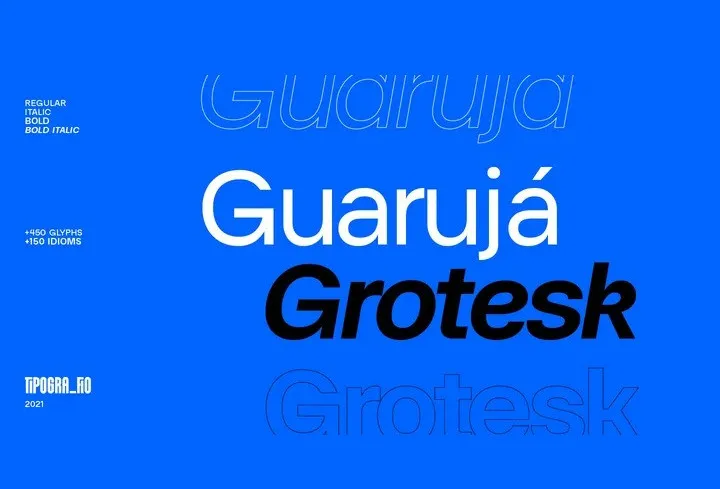
A Guaruja Grotesk Font é uma escolha perfeita para aqueles que desejam incorporar a clássica influência do Modernismo na linguagem visual, numa família de letra sans-serif geométrica e sofisticada. Com proporções inspiradas no estilo modernista da metade do século XX, essa fonte traz elementos góticos distintos, criando uma contraste elegante entre as formas retas e os traços fluidos. Para quem busca layouts brutais ou projetos humanistas sem perder a essência comunicativa, o Guaruja Grotesk é a solução ideal. Além disso, sua versão em itálico oferece um leve desvio círconflexo que promove uma experiência visual mais dinâmica e interessante, perfeitamente adequada para aplicações de headlines ou textos corpos de texto. Escolha essa fonte como seu próximo ponto de partida para uma criação visual impactante e inspiradora.